In diesem Blogbeitrag besprechen wir die 27 besten College-Schriftarten des Jahres 2023, sowohl kostenlose als auch Premium-Optionen.
Egal, ob Sie an einem Schulprojekt arbeiten, eine Broschüre entwerfen oder eine Website erstellen, unsere kuratierte Liste an Schriftarten wird Ihre Designs mit Sicherheit auf die nächste Stufe heben.
Nun fragen Sie sich vielleicht: Warum gerade College-Schriftarten? Nun, College-Schriftarten zeichnen sich durch ihre kühne, klare und zeitlose Ausstrahlung aus.
Sie rufen oft ein Gefühl von Wissenschaft, Tradition und Raffinesse hervor. Durch die Integration dieser Schriftarten in Ihre Designs können Sie sofort die Aufmerksamkeit und Bewunderung Ihres Publikums auf sich ziehen.
Darüber hinaus können Sie bei so vielen verfügbaren Optionen eine Schriftart finden, die perfekt zum Thema und der Stimmung Ihres Projekts passt.
Bevor wir uns mit der Liste befassen, nehmen wir uns einen Moment Zeit, um den Einfluss von Schriftarten auf das Design zu verstehen. Die Wahl der Schriftart kann das Erscheinungsbild eines Stücks völlig verändern. Es kann Emotionen hervorrufen, Botschaften übermitteln und sogar die Lesbarkeit verbessern.
Schriftarten sind nicht nur ein Mittel zur Darstellung von Text; Sie spielen eine entscheidende Rolle bei der Gestaltung der gesamten Designästhetik. Daher ist die Wahl der richtigen Schriftart entscheidend dafür, dass Ihr Projekt hervorsticht und einen bleibenden Eindruck hinterlässt.
Nachdem wir nun die Bedeutung von Schriftarten für das Design verstanden haben, wollen wir uns die 27 besten College-Schriftarten des Jahres 2023 ansehen. Von klassischen Serifenschriften bis hin zu modernen serifenlosen Schriftarten und allem dazwischen haben wir eine Vielzahl von Optionen sorgfältig ausgewählt, um allen Designvorlieben gerecht zu werden.
Egal, ob Sie einen Vintage- oder Retro-Look oder einen eleganten und modernen Stil bevorzugen, in unserer Kollektion sind Sie genau richtig. Lassen Sie uns also eintauchen und die perfekte Schriftart entdecken, die Ihre Projekte zum Strahlen bringt!
Beste Premium-College-Schriftarten
Möchten Sie Ihren Designprojekten das klassische College-Feeling verleihen? Suchen Sie nicht weiter! Unsere Auswahl der besten Premium-College-Schriftarten wird Ihre Designs mit Sicherheit auf die nächste Stufe heben. Lassen Sie sich das nicht entgehen und schauen Sie sich die nachstehenden Empfehlungen an, die Sie unbedingt lesen sollten.
Hochschule
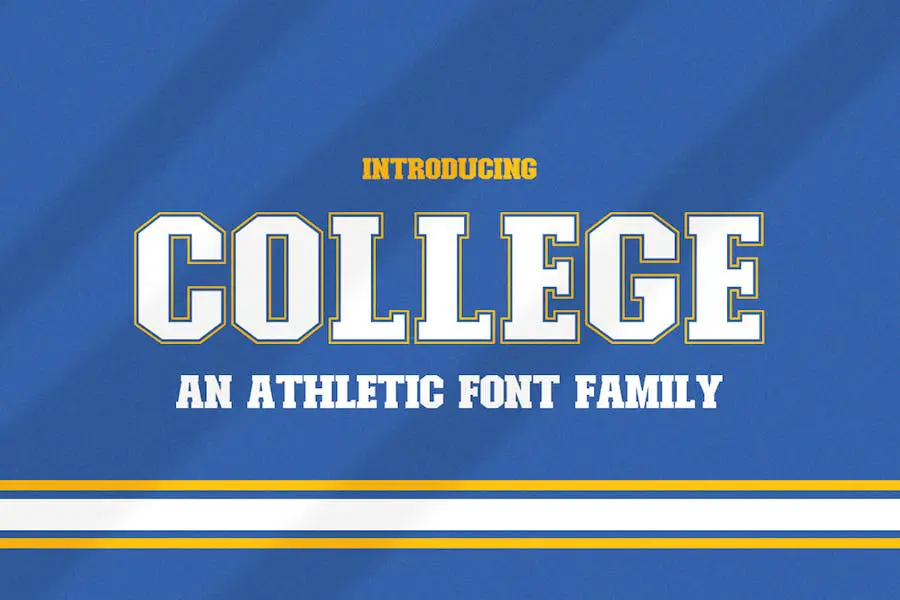
College Fonts ist eine vielseitige Schriftfamilie, die Ihren Designs einen Hauch von Nostalgie und jugendlicher Energie verleiht. Diese Sammlung von Schriftarten ist so konzipiert, dass sie nahtlos zusammenarbeiten und Sie sie kombinieren können, um einzigartige und auffällige Designs zu erstellen.
Egal, ob Sie an einem Schulprojekt, einem Sportplakat oder einem Logo-Design arbeiten, bei College Fonts sind Sie an der richtigen Adresse.
Freshman College
Freshman College ist eine achteckige Serifenschrift, die von Uni-, College- und Militärstilen inspiriert ist. Diese Schriftart eignet sich perfekt für sportbezogene Projekte, Schulen, Ausstellungsarbeiten, Zitate, Poster, Akronyme und Überschriften.
Sein einzigartiges Design verleiht jedem Grafikdesign-Projekt eine mutige und wirkungsvolle Note. Egal, ob Sie ein Logo für eine Sportmannschaft entwerfen oder einen Schulflyer entwerfen, das Freshman College wertet Ihr Projekt auf und verleiht ihm ein unverwechselbares, sportliches Flair.
Mit ihrer vielseitigen Verwendung und ihrem auffälligen Erscheinungsbild ist diese Schriftart ein Muss für jeden Grafikdesigner, der seine Designs aufwerten möchte.
Das Trikot
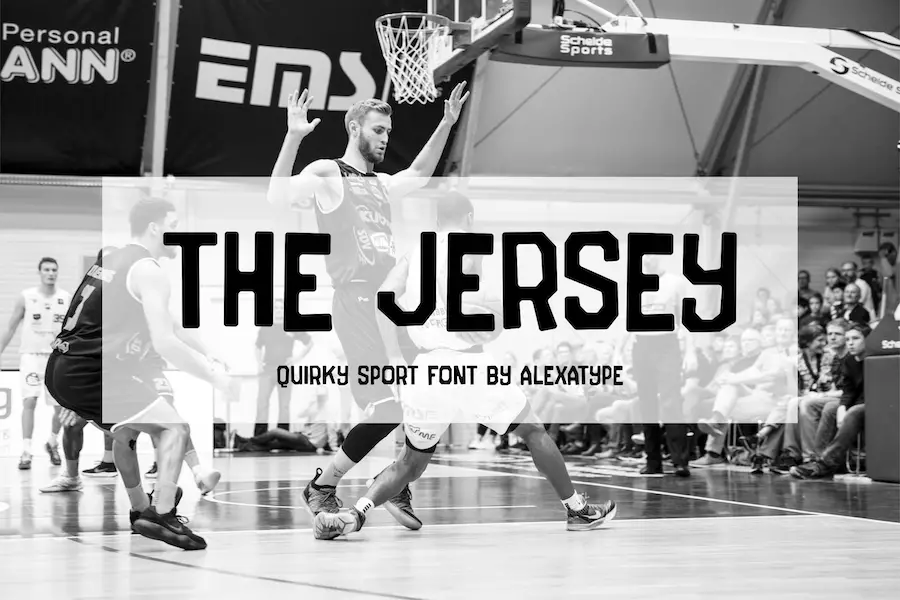
Die Jersey ist eine Schriftart, die die Stärke und Solidität einer traditionellen College-Schriftart mit einem verspielten und rebellischen Touch kombiniert. Mit seiner federnden Grundlinie, der unregelmäßigen Breite und den runden Ecken verleiht es Ihren Designs ein Gefühl von Eigenartigkeit.
Das ausschließlich in Großbuchstaben geschriebene Format trägt zu seiner Ernsthaftigkeit bei und behält gleichzeitig eine jugendliche und energiegeladene Atmosphäre bei. Diese Schriftart ist perfekt, um der schnelllebigen und geschäftigen College-Welt etwas Spaß und Persönlichkeit zu verleihen.
Darüber hinaus bietet es Unterstützung für mehrere Sprachen, was es zu einer vielseitigen Wahl für Designer aus der ganzen Welt macht.
Wilde Katze
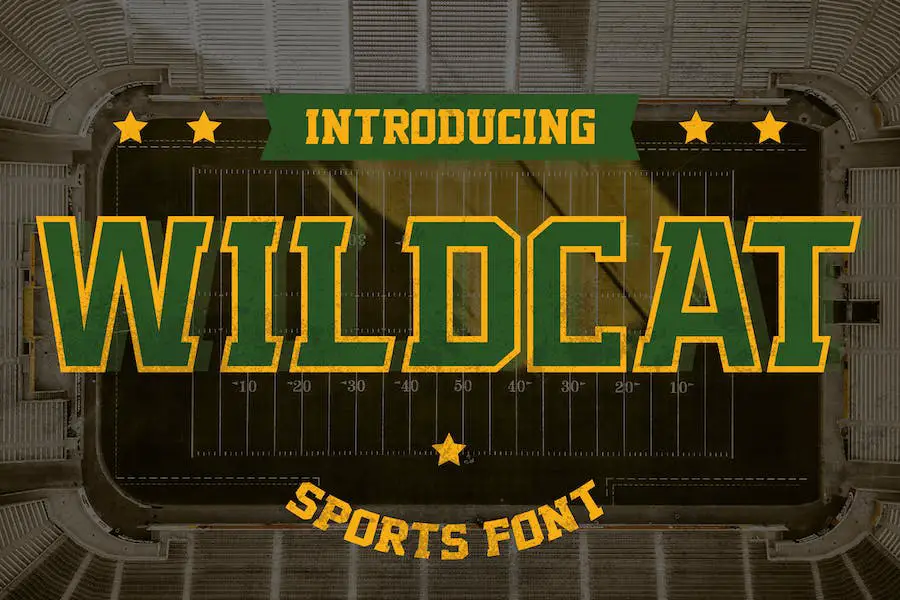
Wildcat ist eine vielseitige Sportschrift, die Ihre sportbezogenen Designprojekte aufwerten wird. Egal, ob Sie ein fesselndes Logo, auffällige Poster, stilvolle Kleidung oder aufmerksamkeitsstarke Schlagzeilen erstellen, Wildcat hat alles für Sie.
Mit seinem kühnen und kraftvollen Look ist es die perfekte Wahl für Basketball-, Fußball-, Softball-, Baseball-, Fußball- und Hockey-Designs.
Sie können es auch verwenden, um Ihre Zeitschriften, Briefpapier, Etiketten, Abzeichen und vieles mehr aufzuwerten. Verleihen Sie Ihren Projekten noch heute mit Wildcat einen mutigen und dynamischen Touch!
Courage Union
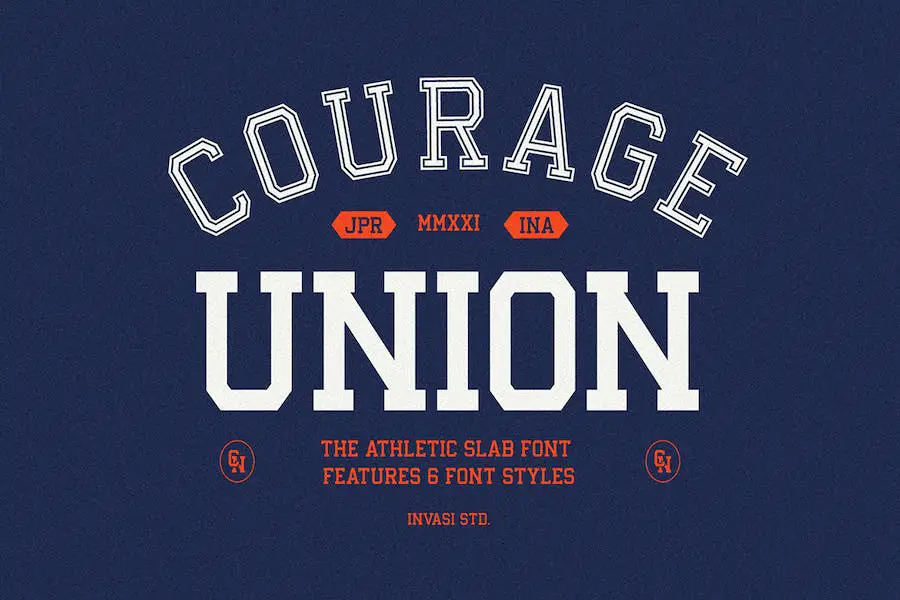
Courage Union – eine It-Schrift, die von Vintage-Sportbekleidung inspiriert ist und mit einem Vintage-Sportgefühl entworfen wurde. Diese Slab-Serif-Schriftart bietet sechs Varianten, darunter Normal, Grob, Halbton, Umriss, grober Umriss und Halbton-Umriss.
Mit sorgfältig gestalteten Stilen eignet sich Courage Union perfekt für Logos, Social-Media-Inhalte und zur Unterstützung Ihrer Lieblingssportmannschaft.
Auslösen
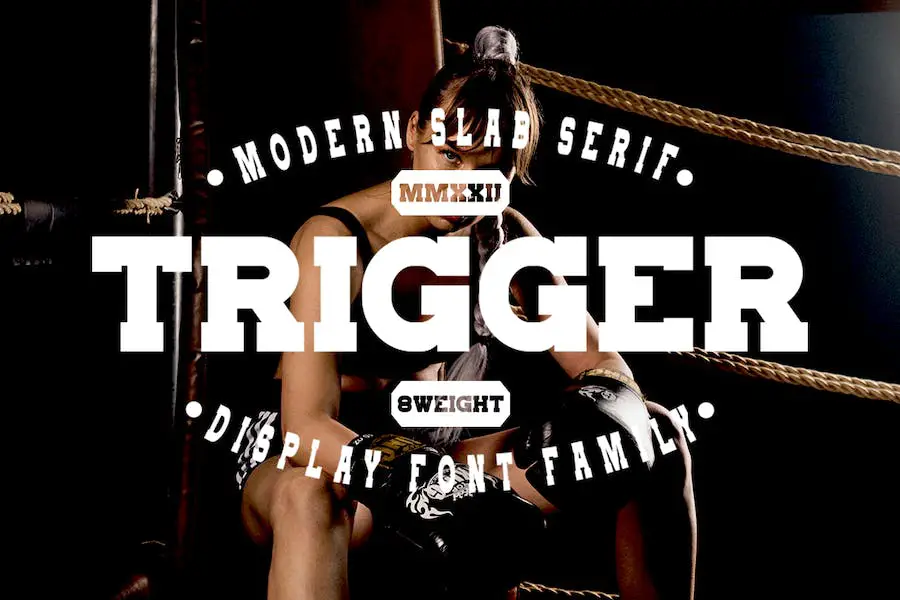
Trigger ist eine Slab-Serif-Schriftart, die von sportlichen und Vintage-Designs mit einem Hauch von klassischem Stil inspiriert ist. Mit 8 verschiedenen Stilen zur Auswahl ist diese Schriftart unglaublich vielseitig und kann jedes Designprojekt aufwerten.
Es kombiniert solide Grundlagen, auffällige Optik, einen Hauch von Old-School-Bewegung und einen modernen, minimalistischen Stil. Egal, ob Sie an einem sportbezogenen Projekt, einem Poster, Branding-Materialien oder sogar Albumtiteln arbeiten, Trigger ist die perfekte Wahl.
Seine kühne und dynamische Ästhetik macht es ideal für Jersey-Drucke, Logo-Design, Bekleidungs-Branding, Produktverpackungen, Zeitschriftentitel und mehr. Diese Schriftart vereint mühelos die Themen Sportlichkeit und Stil und verleiht Ihren Projekten ein einzigartiges und auffälliges Aussehen.
HEIMDAL
HEIMDAL ist eine neue serifenlose Schriftart namens „It!“. das 8 verschiedene Stile in einer Schriftfamilie bietet. Inspiriert von traditionellen minimalistischen Zeichen ist diese Schriftart modern, futuristisch, minimalistisch und klar.
Mit Groß- und Kleinbuchstaben, Zahlen und Satzzeichen bietet es endlose kreative Möglichkeiten. Ob Sie auffällige Schlagzeilen, Logos oder jede Art von Grafikdesign für Web, Print oder Motion Graphics entwerfen, HEIMDAL ist perfekt.
Es eignet sich auch hervorragend zum Erstellen von Postern, Flyern, Branding, Verpackungen und Piktogrammen. Diese Schriftart ist ein Muss für jeden Grafikdesigner, der seinen Projekten einen Hauch von Stil und Einzigartigkeit verleihen möchte.
Bellstead
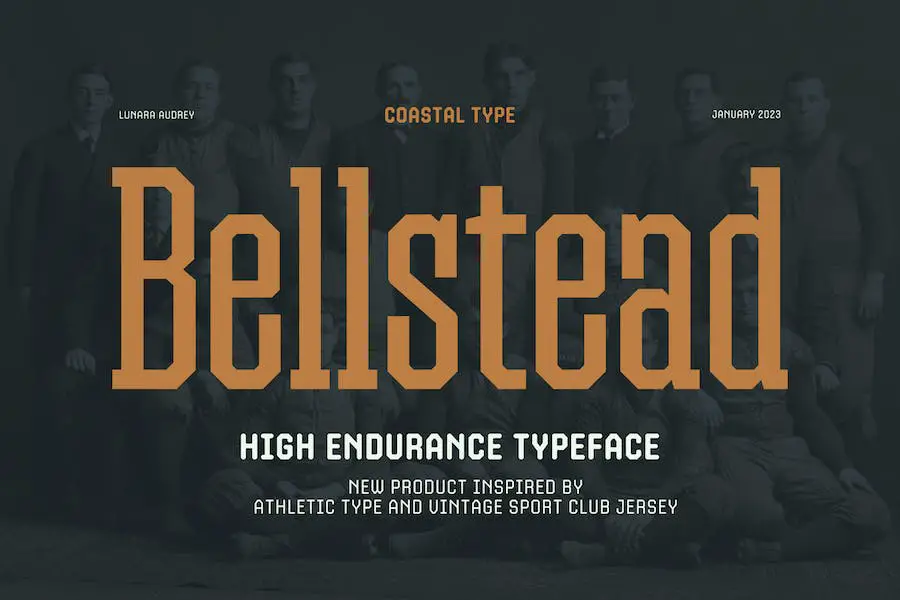
Bellstead ist eine erstaunliche Vintage-inspirierte sportliche Display-Schriftart, die Ihre Designprojekte wirklich aufwerten kann.
Mit seinem kühnen und dynamischen Stil eignet es sich perfekt für verschiedene Anwendungen wie Sportgrafiken, Teamlogos, Schulprojekte und auffällige Displays.
Egal, ob Sie motivierende Zitate, fesselnde Poster oder aufmerksamkeitsstarke Überschriften erstellen, Bellstead liefert die Wirkung, die Sie brauchen. Seine Vielseitigkeit kommt durch die nahtlose Integration von Akronymen zum Ausdruck und fesselt die Aufmerksamkeit durch seine kühne Präsenz.
Grusiaq
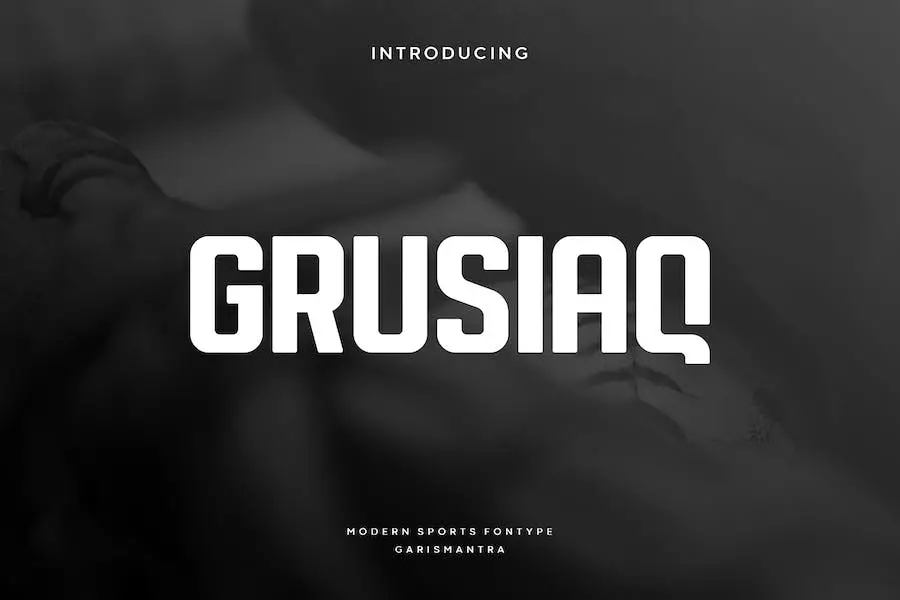
Grusiaq ist eine dekorative Schrift, die Elemente des klassischen und modernen Designs vereint. Mit seinem minimalistischen Stil und den abgerundeten Akzenten verleiht es jedem Projekt eine einzigartige Note.
Diese Großbuchstabenschrift eignet sich perfekt zum Erstellen von Logos, Überschriften und Titeln, insbesondere für sportbezogene Themen. Holen Sie sich noch heute Grusiaq, um Ihrer Kreativität freien Lauf zu lassen und Ihren Designs einen frischen, einzigartigen Look zu verleihen.
College-Block
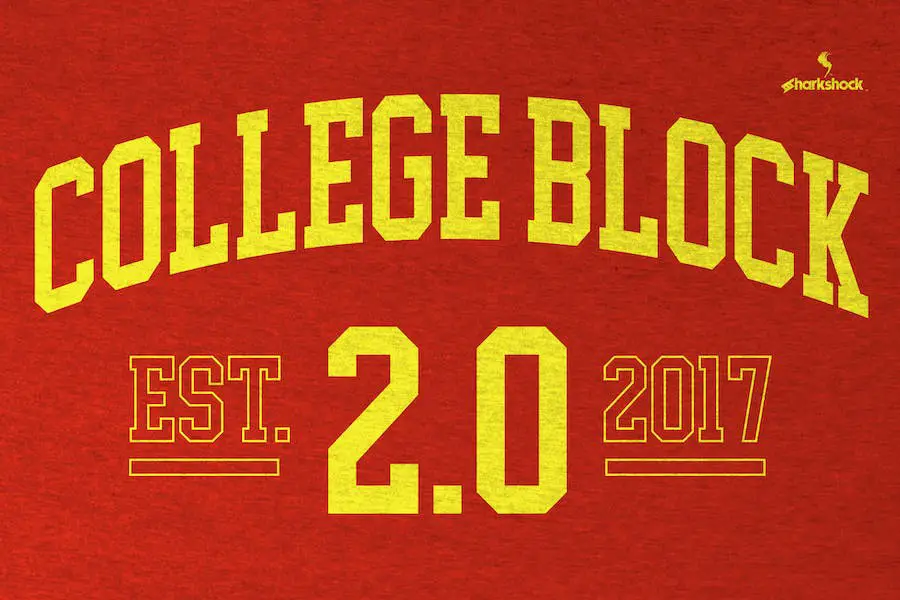
College Block, eine überarbeitete Schriftart mit verbesserter Glyphen- und Sprachunterstützung, ist eine blockige Anzeigeschriftart, die jedem Projekt einen Hauch von Raffinesse verleiht. Mit abgewinkelten Linien und kurzen Serifen gibt es jetzt auch eine 3D-Version für zusätzliche Tiefe.
Die Zeichen sind größer und dünner, was den Kontrast und die Lesbarkeit verbessert. Darüber hinaus enthält diese Schriftart neu gestaltete Zeichen für europäische Akzente sowie Unterstützung für Kyrillisch und andere europäische Sprachen.
Egal, ob Sie ein T-Shirt, ein Logo oder Webgrafiken entwerfen, College Block 2.0 ist eine vielseitige Wahl, die Ihre Designs mit seinem einzigartigen Stil aufwertet.
Behover College
Behover College ist eine fantastische Schriftart, die Kühnheit mit einem Sans-Stil verbindet. Es verfügt über eine Mischung aus Klein- und Großbuchstaben, was es einfacher macht, Designs zu erstellen, die sowohl auffällig als auch ausdrucksstark sind.
Diese Schriftart eignet sich perfekt zum Erstellen von Logos, Sportlogos und allem anderen, was eine herausragende Darstellung oder Überschrift erfordert. Probieren Sie es aus und genießen Sie die Kraft mutigen Designs!
Brown College
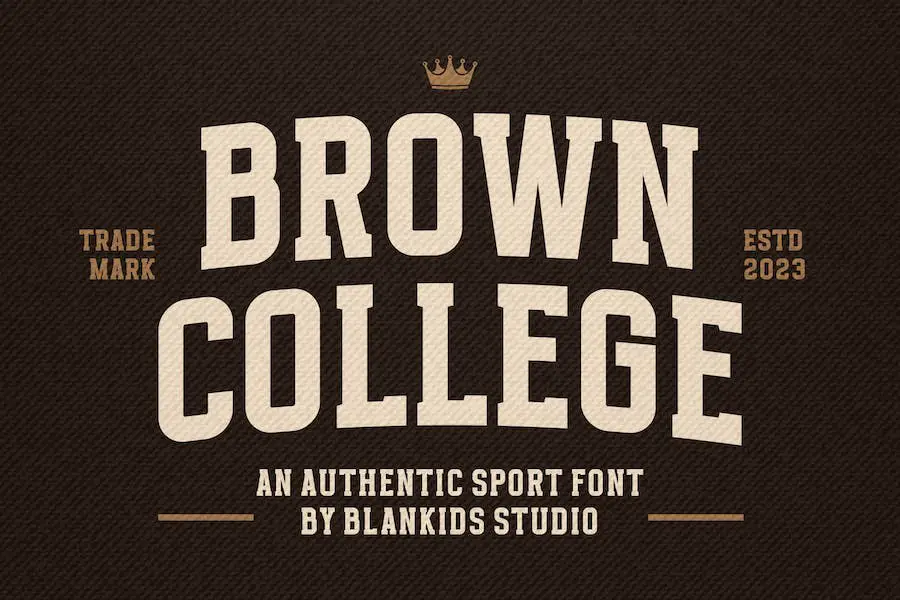
Brown College ist eine authentische Sportschrift, die von der College-Typografie inspiriert ist. Es verleiht jedem Design eine attraktive und verspielte Note und eignet sich perfekt für Buchumschläge, Poster, Verpackungen, Merchandise-Artikel, Logos und mehr.
Mit ihrem hohen Maß an Ästhetik wird diese Schriftart Ihre Projekte mit Sicherheit hervorheben und Kreativität, Fantasie und endlosen Spaß anregen.
Wenn Sie eine einzigartige und auffällige College-Schriftart benötigen, sind Sie bei Brown College genau richtig. Es ist die beste Wahl, um Ihre Designs auf die nächste Stufe zu heben.
UNI Nord
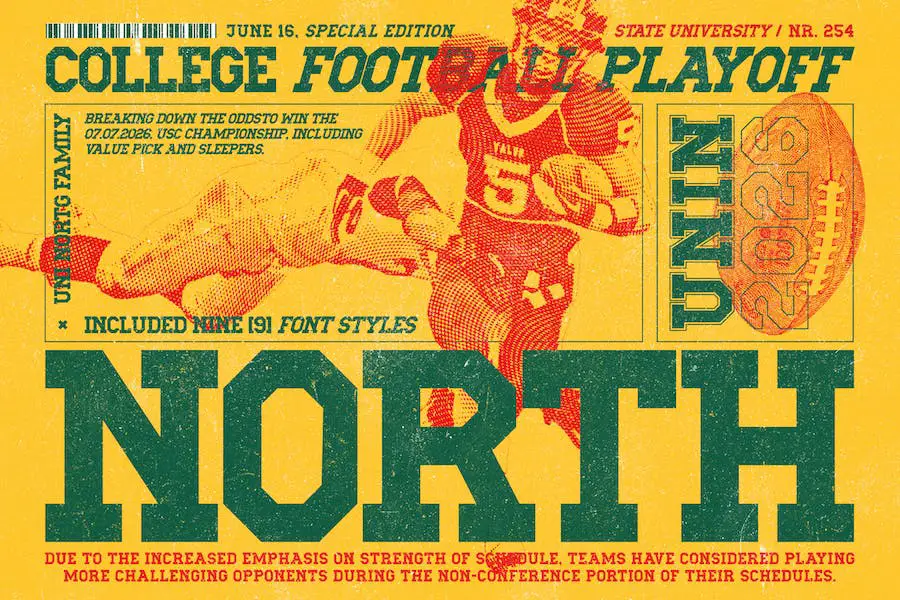
UNI North ist eine handgefertigte Vintage- und Slab-Serif-Schrift, die sich perfekt für Grafikdesigner eignet, die ihre Projekte aufwerten möchten.
Diese Schriftart ist vom Hochschulsport, Retro-Plakaten und Werbung aus den 70er bis 90er Jahren inspiriert. Mit seiner nostalgischen Ausstrahlung verleiht UNI North jedem Design einen Hauch von zeitlosem Charme.
Eine der herausragenden Eigenschaften von UNI North ist seine Vielseitigkeit. Egal, ob Sie an einem Großprojekt arbeiten oder etwas Kleineres und Komplizierteres erstellen, diese Schriftart liefert Ihnen alles.
Radley
Radley ist eine urbane Großbuchstabenschrift namens Radley, die sich perfekt für Sport-Branding und Logos eignet. Es gibt vier verschiedene Stile, die Ihnen zahlreiche Optionen bieten, um Ihren Projekten ein fantastisches Aussehen zu verleihen. Holen Sie sich jetzt Radley und bringen Sie Ihre Designs auf die nächste Stufe!
Killecthrone
Killecthrone ist eine Schriftart, die die Essenz des klassischen College-Stils einfängt, jedoch mit einem modernen und futuristischen Touch.
Es ist von den traditionellen Schriftarten inspiriert, die an Universitäten und Hochschulen verwendet werden, und verleiht der Schriftart durch die Einbindung eines Leiterplattenmusters (PCB) eine einzigartige Note.
Diese Kombination ergibt eine Schriftart, die sowohl nostalgisch als auch modern ist und sich perfekt für Grafikdesigner eignet, die ihren Projekten einen Hauch von Raffinesse und Innovation verleihen möchten.
Brockies
Brockies ist eine sportliche und elegante Schriftart mit einem starken College-Stil. Es ist von beliebten Designtrends inspiriert und somit die perfekte Wahl für jedes Projekt der Moderne. Mit ihren dicken und robusten Buchstaben hat diese Schriftart eine Seele, die Ihre Ideen zum Leben erweckt.
Bronzier
Bronzier ist eine Schriftart, die Grafikdesignern mit ihrem starken Serifenstil dabei helfen soll, ihre Projekte aufzuwerten. Mit 8 verschiedenen Stilen zur Auswahl eignet es sich für verschiedene Designelemente wie Logos, Bekleidung, Poster und mehr.
Diese Schriftart vereint sportliche, Vintage- und moderne Ästhetik und verleiht Ihren Designs ein vielseitiges und dynamisches Aussehen. Inspiriert von der Typografie der alten Schule und mit einem modernen Touch verleiht Bronzier jedem Projekt einen Hauch von Männlichkeit und Raffinesse.
Universität
„Univarsity ist eine Sport-Display-Schriftart, die Ihre Projekte hervorheben soll.“ Mit seinem hohen und aggressiven Aussehen verleiht es jedem Design einen Hauch von Energie.
Ganz gleich, ob Sie Schlagzeilen, Banner, Titel, Poster, Typografie oder Wortmarken erstellen, diese Schriftart wird mit Sicherheit ein Statement setzen. Es eignet sich perfekt für Sportthemen, Sportveranstaltungen, Trikots, E-Sport und Branding-Designs.
Darüber hinaus verfügt es über Groß- und Kleinbuchstaben sowie mehrsprachige Unterstützung für zusätzliche Vielseitigkeit. Verleihen Sie Ihren Designs mit Univarsity eine Extraportion Stil.
Die besten kostenlosen College-Schriftarten
Hallo! Möchten Sie Ihr Grafikdesign-Niveau verbessern? Suchen Sie nicht weiter, denn ich habe genau das Richtige für Sie – die besten kostenlosen College-Schriftarten! Diese Schriftarten eignen sich perfekt, um Ihren Projekten eine stilvolle, akademische Note zu verleihen.
Vertrauen Sie mir, Sie möchten diese Juwelen nicht verpassen. Scrollen Sie also nach unten und entdecken Sie die perfekte kostenlose Schriftart, um Ihre Designs auf die nächste Stufe zu heben. Viel Spaß beim Gestalten!
Bou College
Bou College ist eine vielseitige Schriftart, die jeder Grafikdesigner in seinem Werkzeugkasten haben sollte. Mit seinem klaren und professionellen Erscheinungsbild verleiht Bou College jedem Designprojekt einen Hauch von Raffinesse.
Sein zeitloser Reiz und die eleganten Buchstabenformen machen es perfekt für die Erstellung auffälliger Schlagzeilen, Logos und Branding-Materialien.
Egal, ob Sie an einer eleganten Unternehmensbroschüre oder einem lustigen und verspielten Poster arbeiten, Bou College wertet Ihr Design auf und hebt es von der Masse ab. Diese Schriftart ist die perfekte Wahl für Designer, die ihren Projekten einen Hauch von Klasse verleihen möchten.
College-Junge
College Boy ist eine fantastische Schriftart für Grafikdesigner, die das Design ihres Projekts aufwerten möchten. Mit ihrem schlanken und modernen Design verleiht diese Schriftart jeder visuellen Arbeit einen Hauch von Raffinesse.
Seine klaren Linien und kräftigen Striche machen es perfekt für Schlagzeilen, Titel, Logos und mehr. Mit College Boy hinterlassen Ihre Designs garantiert einen bleibenden Eindruck.
Diese Schriftart verfügt über eine große Auswahl an Zeichen und Glyphen und bietet endlose kreative Möglichkeiten. Sie können Ihren Text anpassen, indem Sie Kerning, Spurweite und Zeilenabstand anpassen, um das gewünschte Aussehen zu erzielen.
Collegerion
Collegerion ist eine Schriftart, die speziell für Grafikdesigner entwickelt wurde, die das Design ihrer Projekte verbessern möchten. Diese von Leonard Posavec von LeoSupply.co erstellte Schriftart bietet eine breite Palette von Eigenschaften, die sie ideal für Designs mit College-Thema machen.
Mit Collegerion können Sie Ihren Projekten einen Hauch von Nostalgie und Authentizität verleihen. Die Schriftart zeichnet sich durch einen Vintage- und Retro-Stil aus, der die Essenz des Universitätslebens perfekt einfängt.
Egal, ob Sie an einem Poster, einem Flyer oder einem anderen Design arbeiten, Collegerion verleiht Ihrer Arbeit ein einzigartiges und auffälliges Aussehen.
College-Star
College Star ist eine Schriftart, die sich perfekt für Grafikdesigner eignet, die ihren Projektentwürfen einen Hauch von College-Stil verleihen möchten. Diese Schriftart verleiht jedem Design eine jugendliche und energiegeladene Atmosphäre und eignet sich daher ideal für Projekte im Zusammenhang mit Bildung, Sport oder allem, was einen Hauch von Schulgeist braucht.
Mit seinen klaren Linien und seiner markanten Präsenz fällt College Star auf und erregt Aufmerksamkeit. Die einfache Lesbarkeit sorgt dafür, dass Ihre Botschaft effektiv und ohne Ablenkungen vermittelt wird.
Egal, ob Sie ein Poster, ein Logo oder sogar eine Website entwerfen, diese Schriftart wertet Ihre Arbeit auf und verleiht ihr das gewisse Etwas.
College-Block
College Block ist eine Schriftart, die speziell für Grafikdesigner entwickelt wurde, die das Design ihrer Projekte verbessern möchten. Diese von Sharkshock erstellte Schriftart hat einen einzigartigen Stil, der jedem Design einen Hauch von Nostalgie und Authentizität verleiht.
Mit seinen kräftigen und blockigen Buchstaben erinnert College Block an den klassischen Uni-Stil, der oft auf Schulsporttrikots und Jahrbuchumschlägen zu sehen ist. Es fängt die Essenz des Colleges ein und bringt sie in die digitale Welt.
Ob Sie ein Poster, ein Logo oder eine Einladung entwerfen, diese Schriftart verleiht Ihrem Projekt einen coolen Vintage-Touch.
Atlanta College
Atlanta College ist eine Schriftart, die speziell für Grafikdesigner entwickelt wurde, die das Design ihrer Projekte verbessern möchten. Diese von Graphicsauceco erstellte Schriftart bietet ein einzigartiges und stilvolles Erscheinungsbild, das sich perfekt für jedes College-inspirierte Design eignet.
Mit dem Atlanta College können Sie Ihren Projekten einen Hauch von Nostalgie und jugendlicher Energie verleihen. Ganz gleich, ob Sie ein Poster, ein Logo oder eine Website erstellen, mit dieser Schriftart können Sie die Essenz des Universitätslebens einfangen.
Die Eigenschaften von Atlanta College heben sie von anderen Schriftarten ab. Seine kräftige und scharfe Schrift verleiht Ihren Designs eine starke und wirkungsvolle Präsenz. Die klaren Linien und geometrischen Formen der Schriftart sorgen für ein modernes und elegantes Aussehen und bewahren gleichzeitig ein Gefühl von Spaß und Kreativität.
ZURÜCK ZUR SCHULE
BACK TO SCHOOL ist eine Schriftart namens „It Font“, die von Billy Argel Fonts erstellt wurde. Diese Schriftart ist perfekt für Grafikdesigner, die ihre Projektdesigns verbessern möchten. Es hat einen einzigartigen Stil, der jedem Design eine verspielte und jugendliche Note verleiht.
Mit „It Font“ können Designer das nostalgische Gefühl des College-Studiums zurückbringen. Die Schriftart fängt die Essenz des College-Erlebnisses ein und eignet sich daher ideal für Projekte im Zusammenhang mit Bildung, Studentenleben oder jedem Design, das einen Hauch jugendlicher Energie benötigt.
„It Font“ zeichnet sich durch ein klares und gut lesbares Design aus, sodass es in verschiedenen Größen gut lesbar ist. Aufgrund seiner Vielseitigkeit kann es sowohl für Überschriften als auch für Fließtexte verwendet werden und gibt Designern die Freiheit, mit verschiedenen Layouts und Kompositionen zu experimentieren.
Radley
Wir stellen vor: Radley – die perfekte Schriftart für Grafikdesigner, die ihre Projekte mit einem Hauch von College-inspiriertem Stil aufwerten möchten. Diese von Billy Argel Fonts erstellte Schriftart wurde speziell entwickelt, um die nostalgische Atmosphäre des Schulanfangs zurückzubringen.
Mit seinen einzigartigen und auffälligen Eigenschaften wird Radley Ihre Designs mit Sicherheit auf die nächste Stufe heben. Radley fängt mit seinen kühnen und verspielten Buchstabenformen die Essenz des College-Erlebnisses ein.
Jeder Charakter wird sorgfältig ausgearbeitet, um Ihren Designs ein Gefühl von Jugendlichkeit und Kreativität zu verleihen. Egal, ob Sie an einem Schulprojekt arbeiten, ein Poster entwerfen oder ein Logo für eine Studentenorganisation erstellen, Radley verleiht Ihrer Arbeit einen frischen und lebendigen Look.
Ranglistensport
Ranked Sports ist eine Schriftart, die speziell für Grafikdesigner entwickelt wurde, die das Design ihrer Projekte verbessern möchten. Diese von variatype erstellte Schriftart bietet einen modernen und eleganten Look, der sich perfekt für Designs mit Sportthemen eignet.
Mit Radley Sans Font können Sie Ihrer Arbeit ein Gefühl von Professionalität und Stil verleihen. Zu seinen Merkmalen gehören ein klares und stromlinienförmiges Design, einfache Lesbarkeit und Vielseitigkeit, die eine Verwendung für verschiedene Zwecke ermöglicht.
Egal, ob Sie ein Logo, ein Poster oder eine Website entwerfen, Ranked Sports ist die Schriftart, die Ihre Projekte auf die nächste Stufe hebt.
Häufig gestellte Fragen
College-Schriftarten sind ein Schriftstil, der häufig mit Universitäten und Bildungseinrichtungen in Verbindung gebracht wird. Diese Schriftarten haben oft einen klassischen, Vintage- oder College-Look, der ein Gefühl von Tradition und Wissenschaft hervorrufen kann.
Sie können College-Schriftarten in verschiedenen Designprojekten verwenden, um einen Hauch von akademischem Flair zu verleihen. Sie können in Logodesigns, Veranstaltungsplakaten, Flyern, Abschlusseinladungen und sogar auf Websites oder Social-Media-Grafiken verwendet werden.
Es ist jedoch wichtig, diese Schriftarten mit Bedacht zu verwenden und sicherzustellen, dass sie mit der gesamten Designästhetik und dem Zweck Ihres Projekts übereinstimmen.
College-Schriftarten erfreuen sich aufgrund ihrer Fähigkeit, ein Gefühl von Nostalgie, Tradition und Intellektualität zu vermitteln, zunehmender Beliebtheit. Sie werden häufig in verschiedenen Designprojekten wie Logos, Postern und Einladungen verwendet, um eine akademische oder universitäre Atmosphäre zu schaffen.
Abschluss
Abschließend haben wir die 27 besten College-Schriftarten für 2023 untersucht, sowohl kostenlose als auch Premium-Schriftarten. Wir haben darüber gesprochen, wie wichtig es ist, die richtige Schriftart auszuwählen, um Ihre Designprojekte aufzuwerten und ein professionelles und fesselndes visuelles Erlebnis zu schaffen.
Ganz gleich, ob Sie eine College-Broschüre, einen Studenten-Newsletter oder ein Campus-Event-Poster erstellen, diese Schriftarten heben Ihre Designs mit Sicherheit auf die nächste Ebene.
Um tiefer in dieses Thema einzutauchen und weitere Einblicke zu gewinnen, schauen Sie sich unbedingt den BetterStudio-Blog an. Unser Blog bietet eine große Auswahl an Tutorials und Ressourcen, die Ihnen helfen, Ihre Designfähigkeiten zu verbessern und über die neuesten Trends auf dem Laufenden zu bleiben.
Egal, ob Sie Anfänger oder erfahrener Grafikdesigner sind, es gibt für jeden etwas zu lernen und zu erkunden.